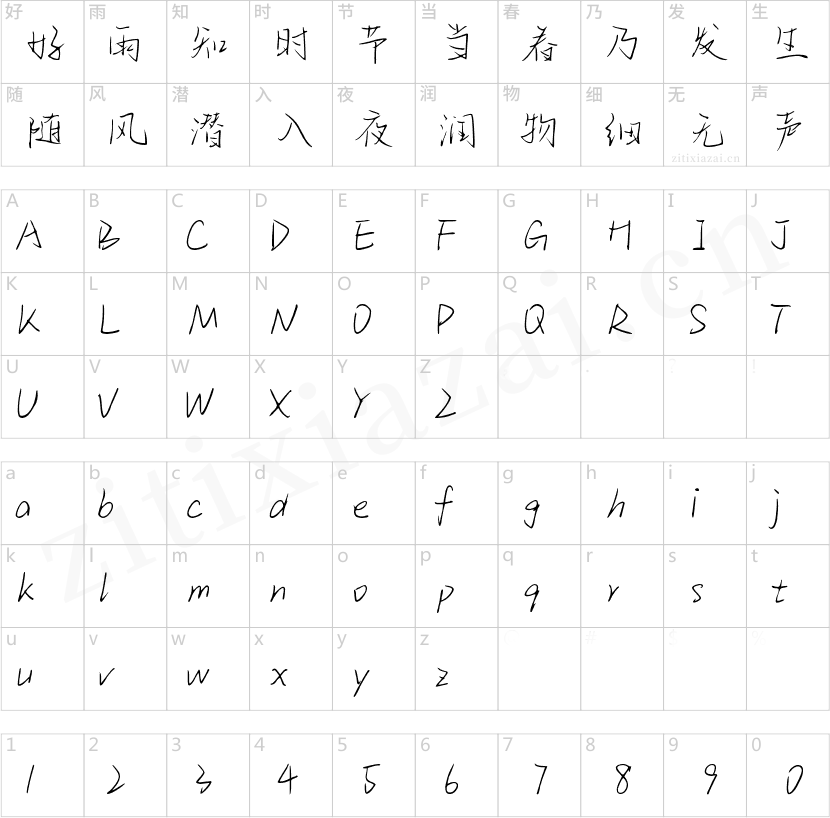
Aa归梦行书
Aa归梦行书字体
Aa归梦行书是一款非常具有艺术性的字体,它的设计灵感来源于对古典艺术的研究,同时又融入了现代字体设计的元素。字形优美,笔画粗细变化自然,给人以大气、典雅的感觉。Aa归梦行书是一款既传统又现代的字体,它的设计充满艺术感,美观大方,实用性也非常强。无论是对于设计师还是对于普通读者来说,都是一种非常不错的字体选择。Aa归梦行书适合用于具有艺术感的场合,比如海报、宣传单张、书籍封面等。由于其字形流畅且具有动态感,也适合用于大量的文本排版,如报纸、杂志等。